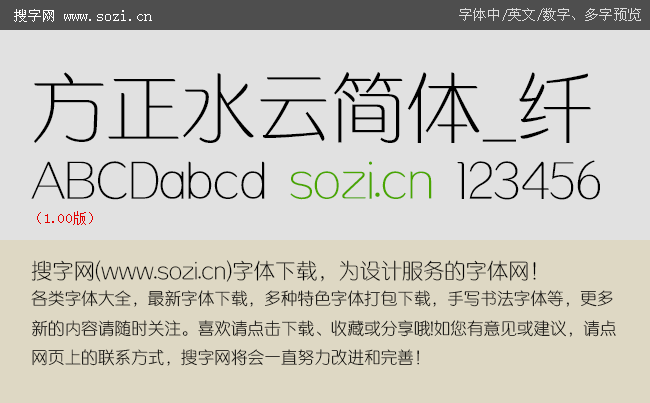
方正水云簡(jiǎn)體_纖
搜字網(wǎng)提供一款方正水云簡(jiǎn)體_纖中文字體下載,方正水云體筆形由至簡(jiǎn)的直線與弧線構(gòu)成,拋棄細(xì)節(jié),追求用最簡(jiǎn)潔元素營(yíng)造豐富而統(tǒng)一的視覺(jué)氛圍。字體簡(jiǎn)潔流暢、圓潤(rùn)柔美,如行云流水般平緩易讀,“水云體”因此意象得名,適用于產(chǎn)品設(shè)計(jì)、包裝印刷、報(bào)刊雜志、正文標(biāo)題、繪畫(huà)創(chuàng)作等廣告設(shè)計(jì)場(chǎng)合使用。